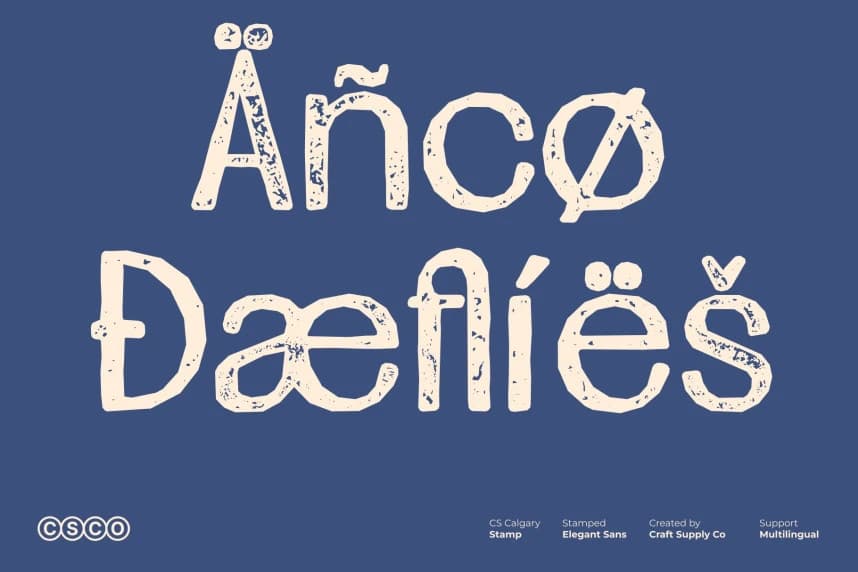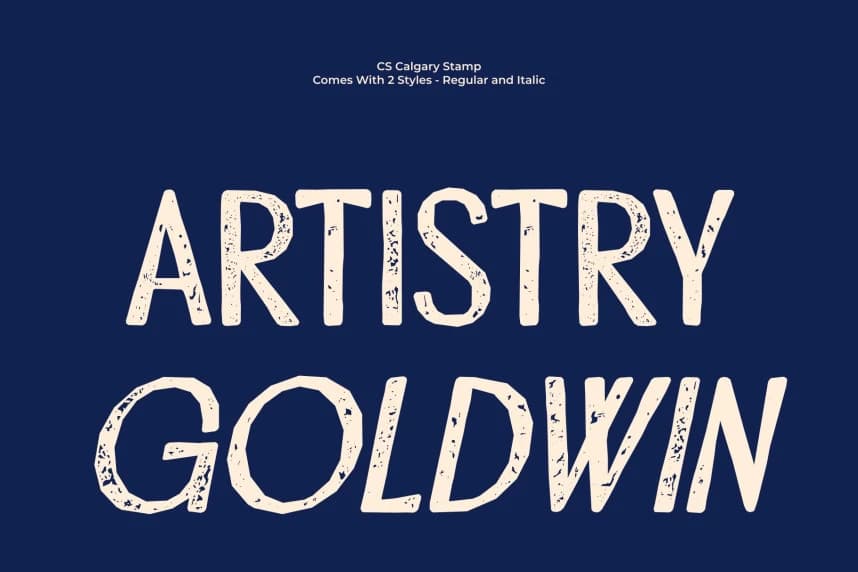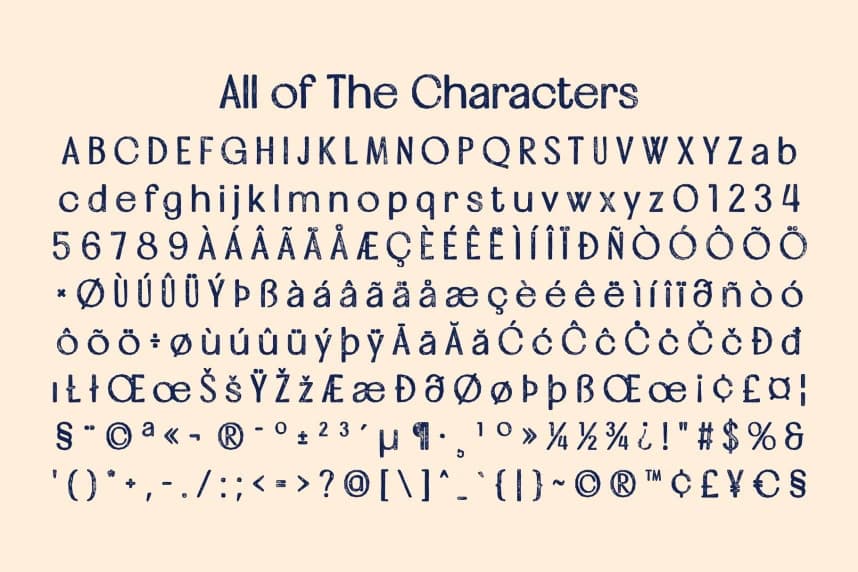
CS Calgary Stamp Font
CS Calgary Stamp Font – Vintage Damga Karakteriyle Minimalist Lüks, Modern Sans Serif ile Zamansız Doku Buluşması. Bu, minimalist zarafeti ile damga etkisinin dokunsal çekiciliğini bir araya getirir.
CS Calgary Stamp Font – Vintage Damga Karakteriyle Minimalist Lüks ve Modern Sans Serif, Zamansız Doku ile Buluşuyor. Bu, minimalist zarafeti ile damga etkisinin dokunsal cazibesini bir araya getirir.